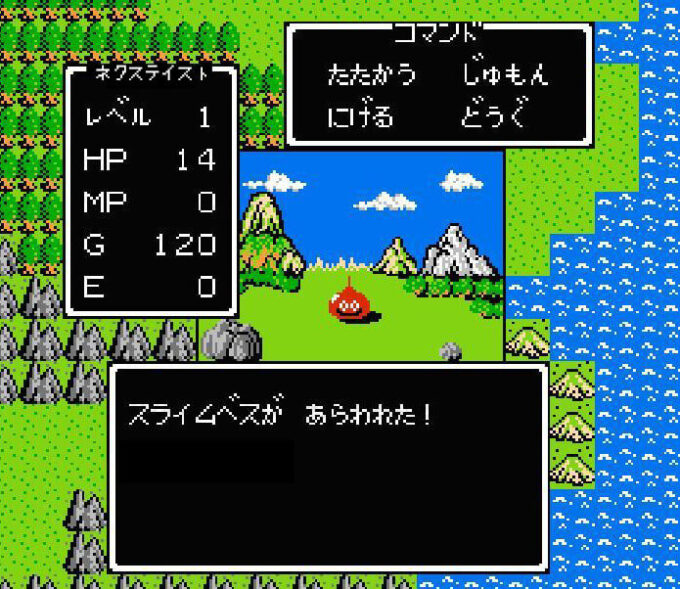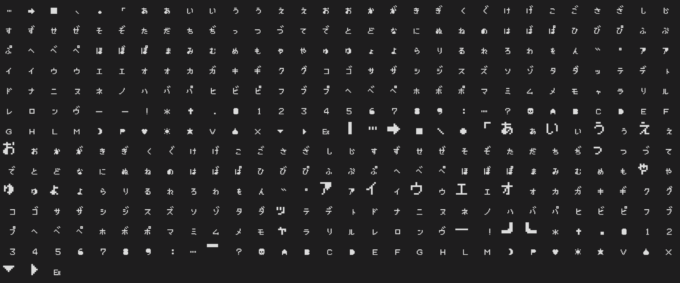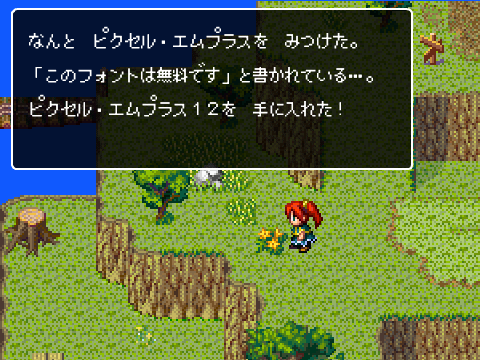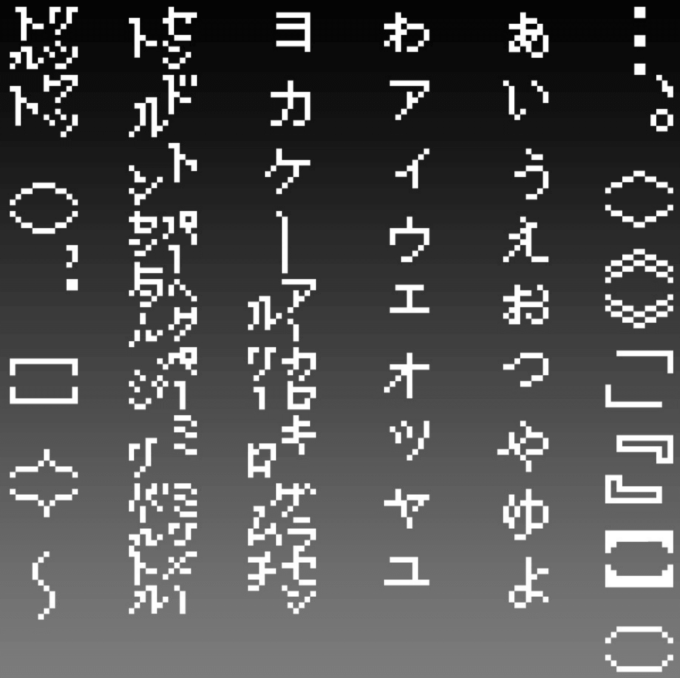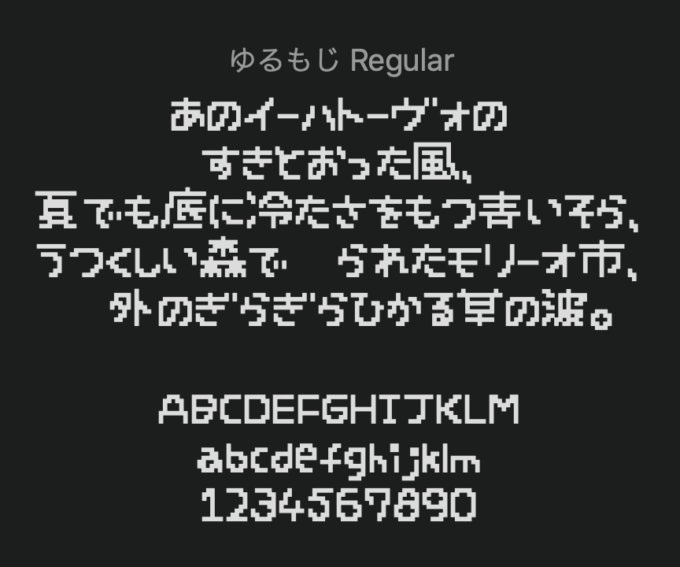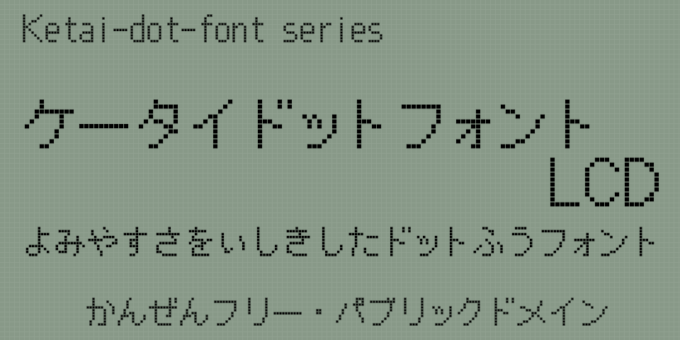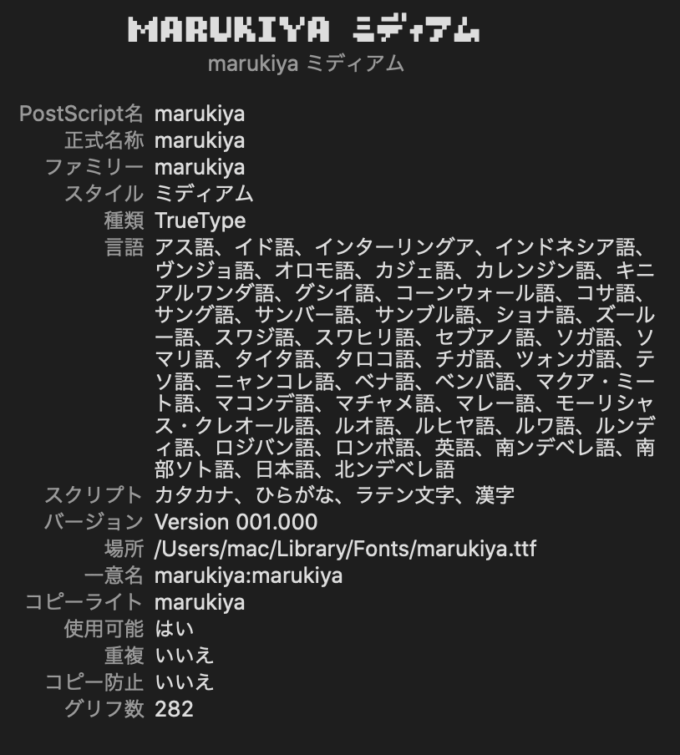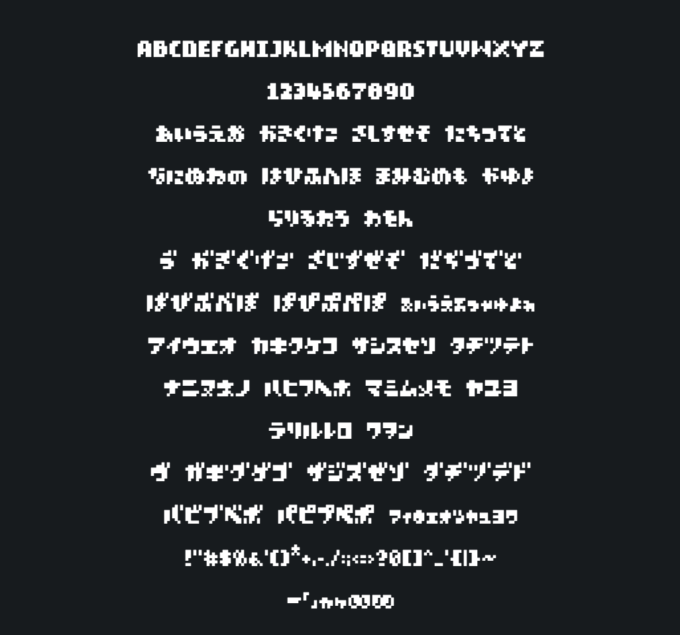
今回は懐かしのテレビゲームのようなレトロな表現ができるビットマップフリーフォントをまとめて紹介していきます。
ビットマップフリーフォントまとめ
テレビゲームのようなレトロな表現ができるビットマップフリーフォントをまとめて紹介していきます。
ベストテンFONT
ゆるもじ
アナログテレビフォント
まるきやフォント
略字超少ドット12
ノスタルドット(M+)
PixelMplus
DragonQuest
ケータイドットフォント-LCD
Pixelify Sans
The Strong Gamer
美咲ゴシック、美咲明朝
SH Pinscher
Pixbob Lite
4×4極小かなフォント
BIT NEON
じゃっきーふぉんと